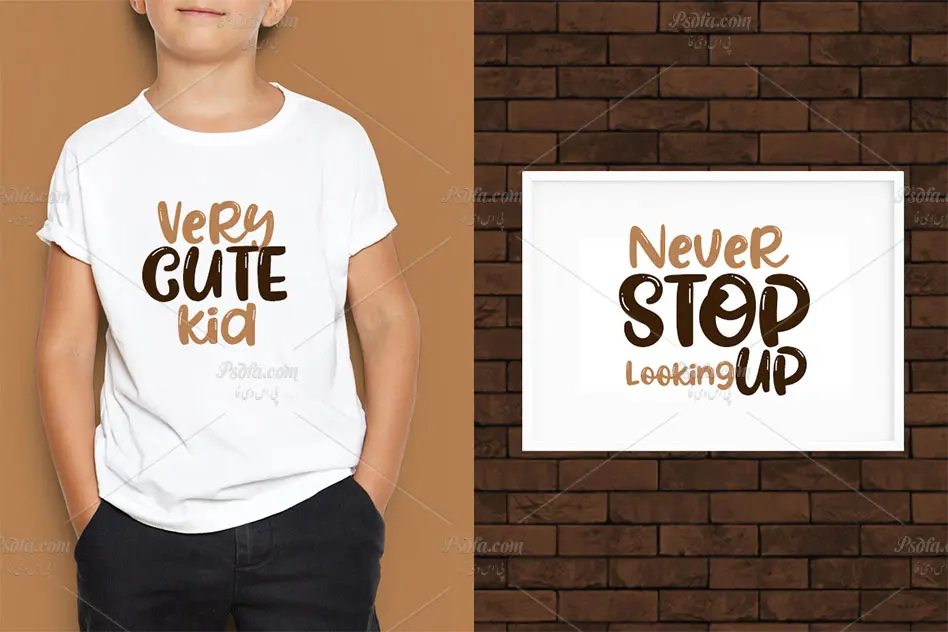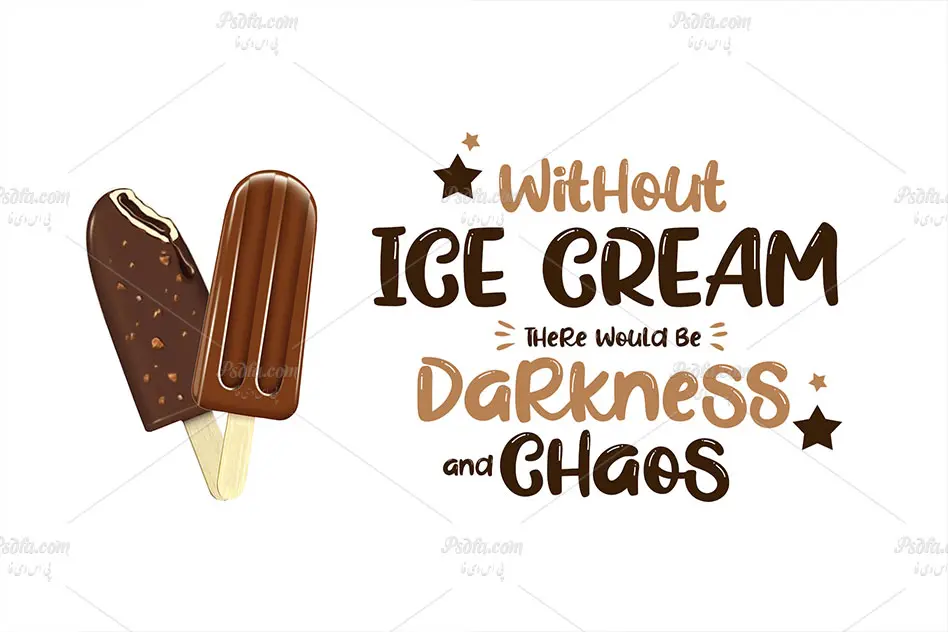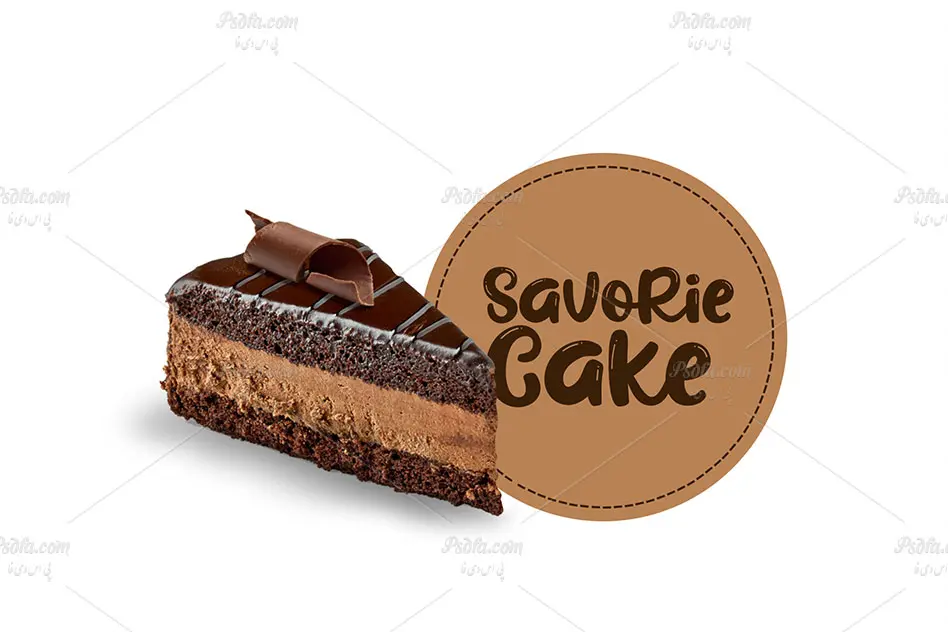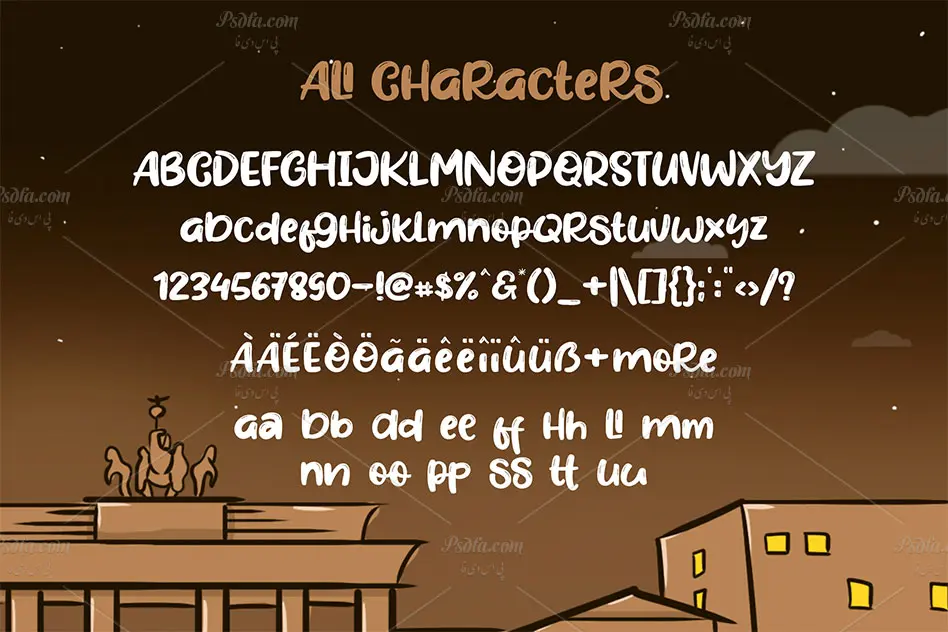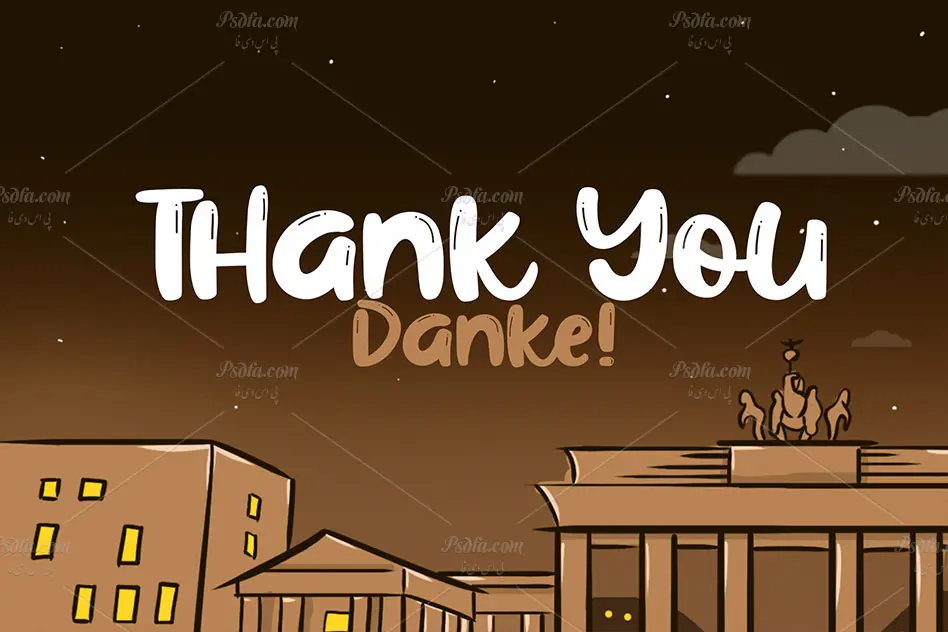
فونت انگلیسی فانتزی و کارتونی Night in Berlin مناسب برای طرح های کودکانه
فونت انگلیسی فانتزی و کارتونی Night in Berlin
در این پست شاهد فونت انگلیسی فانتزی و کارتونی Night in Berlin مناسب جهت استفاده در طرح های کودکانه می باشید. این فونت زیبا در قالب فایل های ttf , otf , woff و woff2 در سایت بارگذاری شده است که پس از نصب یکی از دو فرمت ttf یا otf در پوشه فونت های سیستم قادر به استفاده از آن در تمام نرم افزارهای گرافیکی و ویرایشگر متن از جمله نرم افزار فتوشاپ ، ایلاستریتور ، پریمیر ، مجموعه نرم افزار آفیس و … خواهید بود. فونت Night in Berlin در دو وزن معمولی و کج یا مورب طراحی شده است که بسته به نیاز خود می توانید از هر کدام در طرح های خود استفاده کنید. همچنین اگر طراح صفحات وب باشید از دیگر فرمت های این فونت می توانید در طراحی وب سایت نیز استفاده کنید.